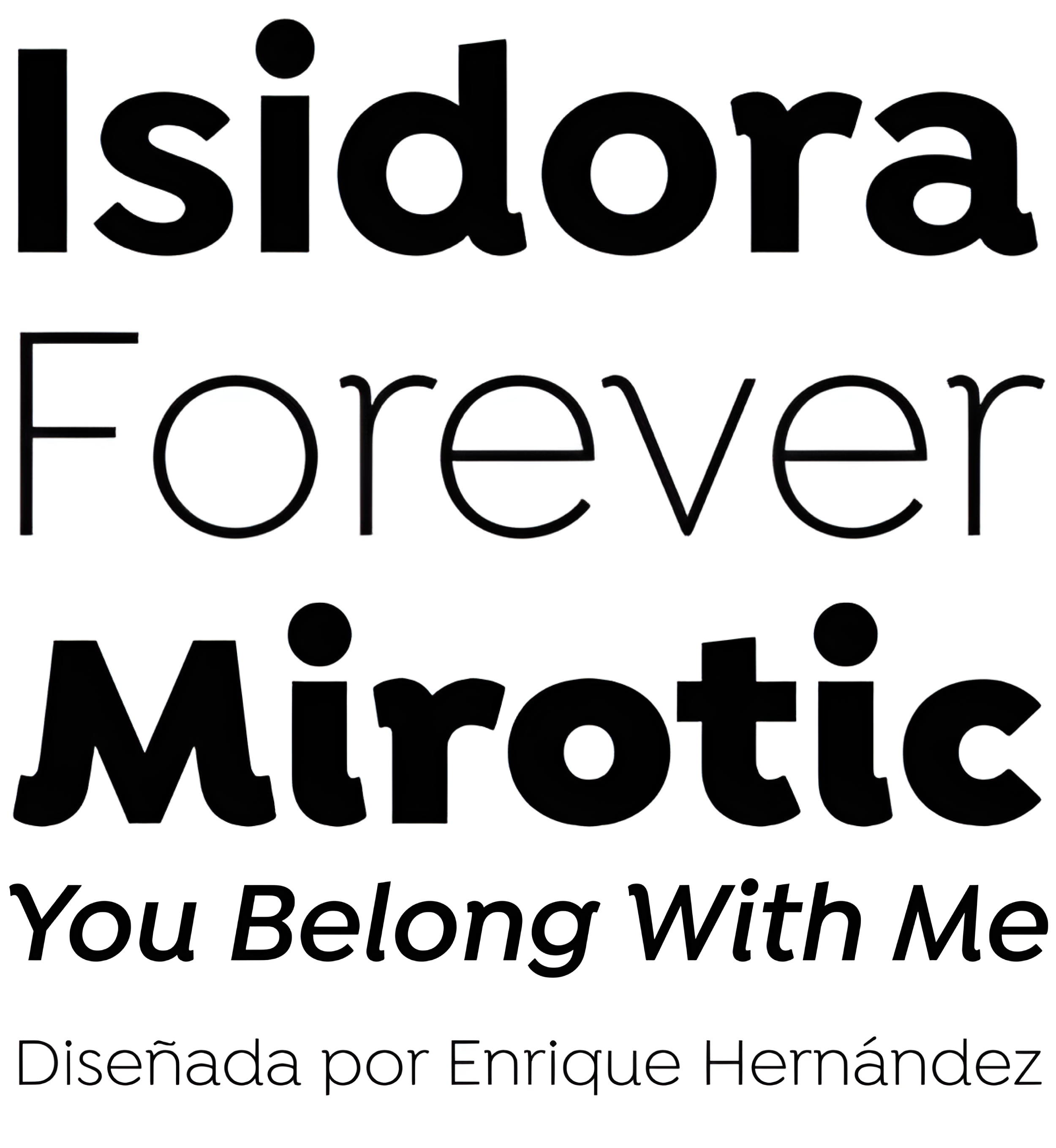
| Año | 2016 |
| Créditos | Enrique Hernández |
| Descripción | Diseñada por Enrique Hernández V. Isidora es un diseño geométrico moderno basado en las typefaces clásicas de los inicios del siglo 20 con un toque contemporáneo y funcional. A pesar de su estructura pesada y racional, la fuente se ve amigable y expresiva, gracias a sus terminaciones redondeadas. Agregado a esto, su corte terminal en diagonal le da una apariencia suave y redondeada. Isidora consiste de dos subfamilias de de 7 pesos: una (más clásica) Regular y una Alternativa (más contemporánea y para uso en display). Ambas subfamilias tienen versión itálica, dando un total de 28 fuentes. Isidora es una tipografía perfecta para titulares, logotipos, branding, packaging, publicaciones y uso web. La familia contiene un set de 438 caracteres - respaldando 207 lenguajes diferentes - e incluye también un set de caracteres alternativos, el que permite más versatilidad al componer un texto. |
| Familia(s) | Thin, Thin Italic, Light, Light Italic, Regular, Regular Italic, Medium, Medium Italic, Semi Bold, Semi Bold Italic, Bold, Bold Italic, Black, Black Italic, Alt Thin, Alt Thin Italic, Alt Light, Alt Light Italic, Alt Regular, Alt Regular Italic, Alt Medium, Alt Medium Italic, Alt Semi Bold, Alt Semi Bold Italic, Alt Bold, Alt Bold Italic, Alt Black, Alt Black Italic |
| Estilos | 28 |